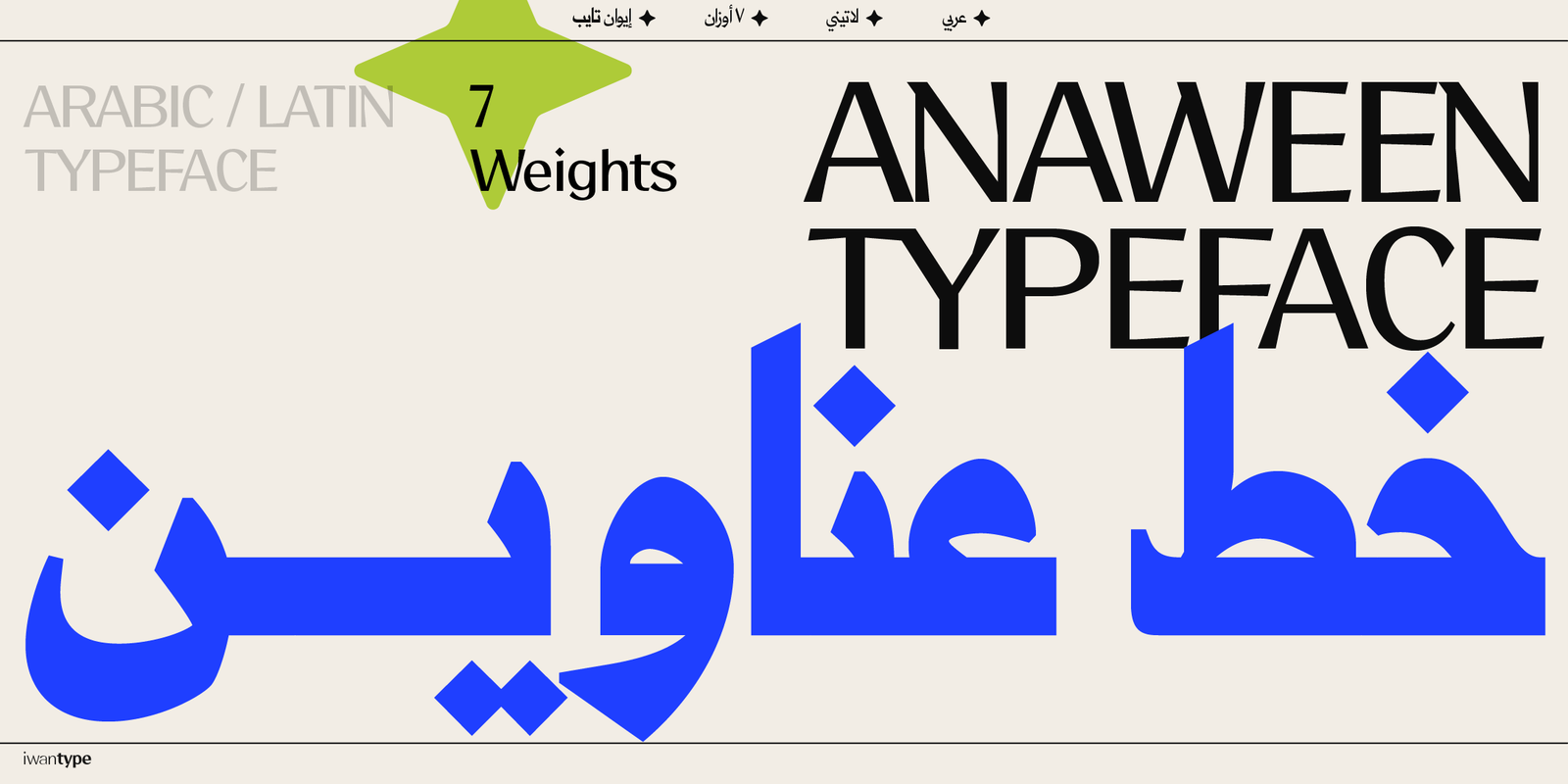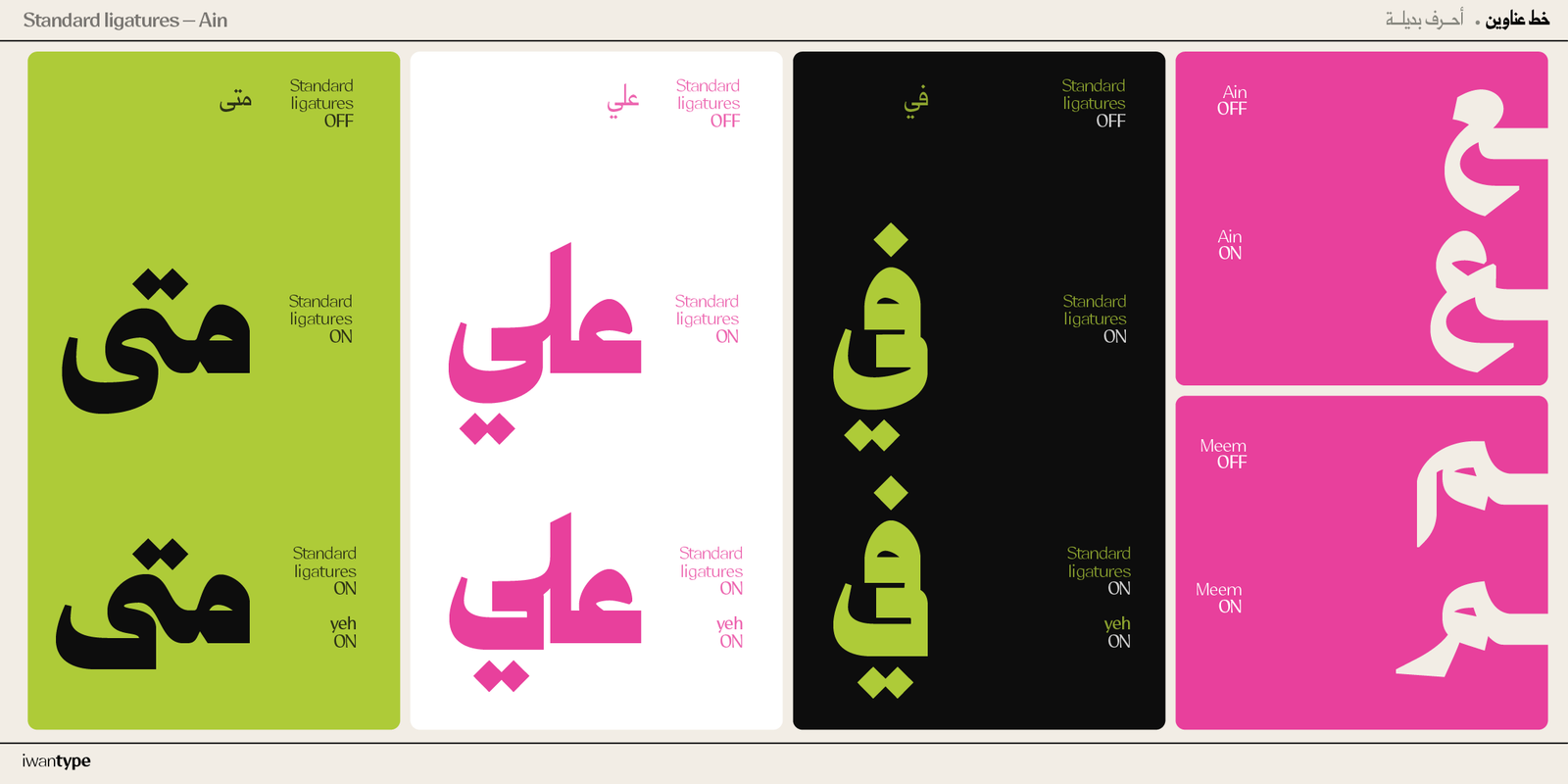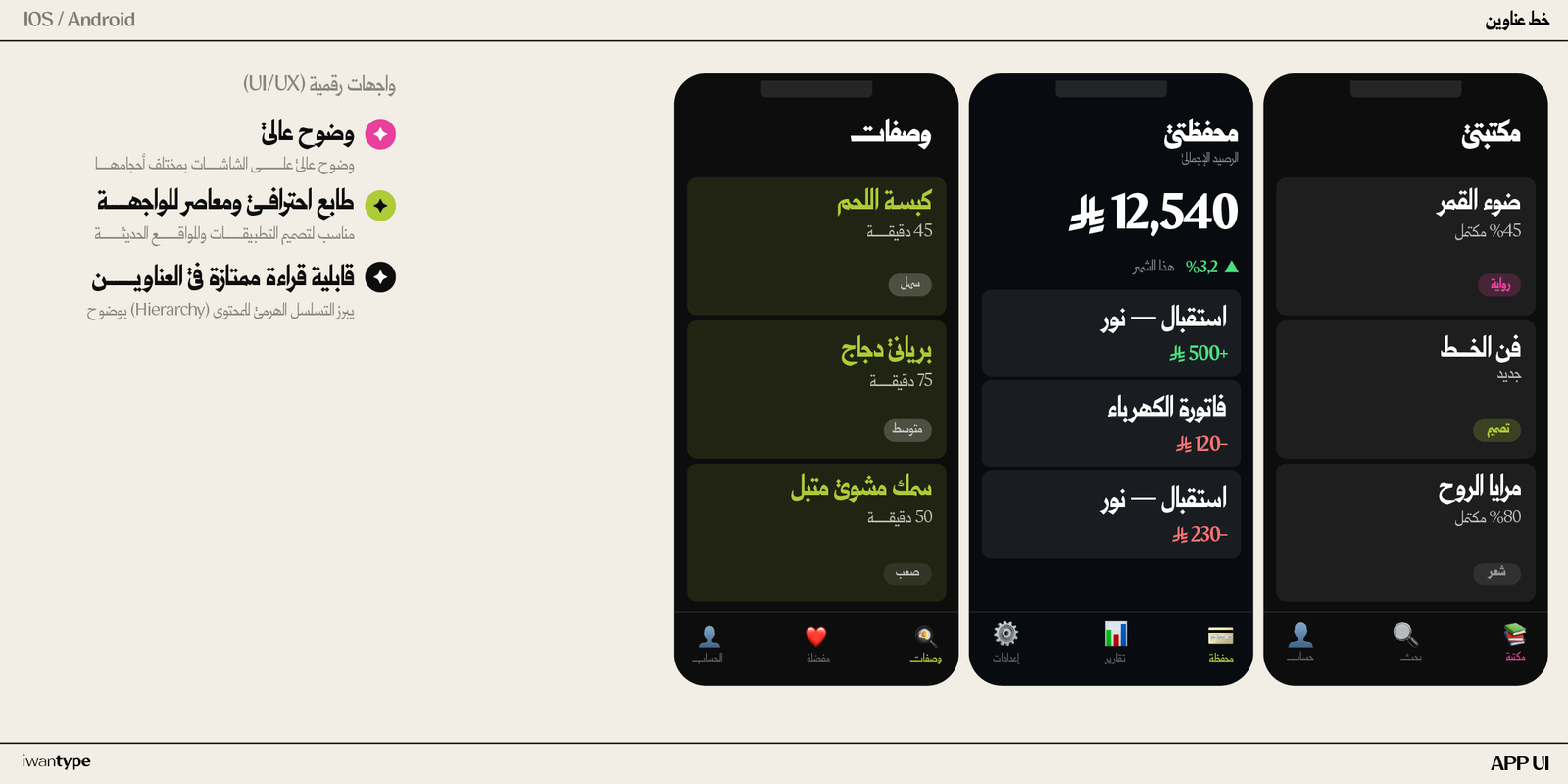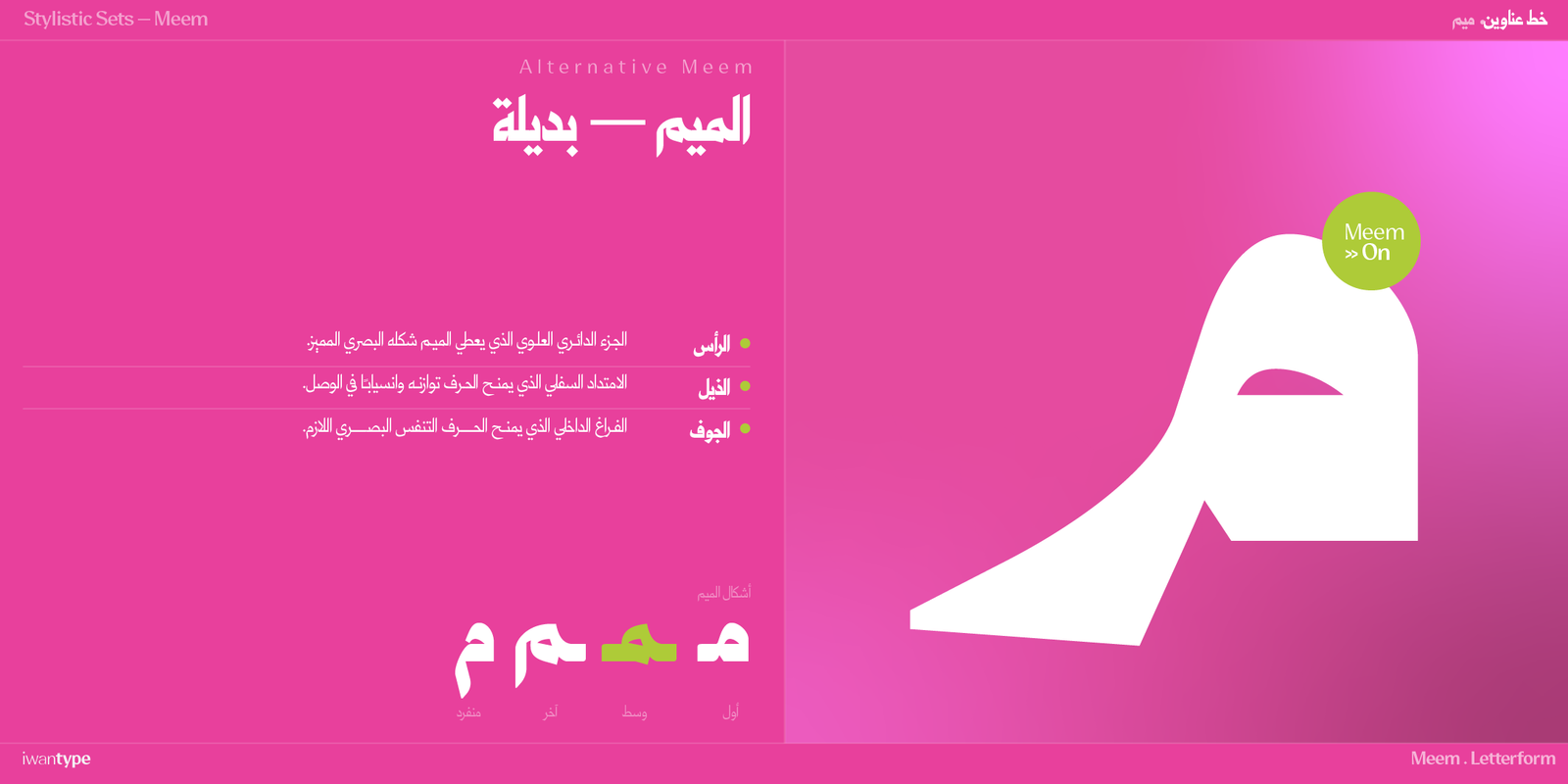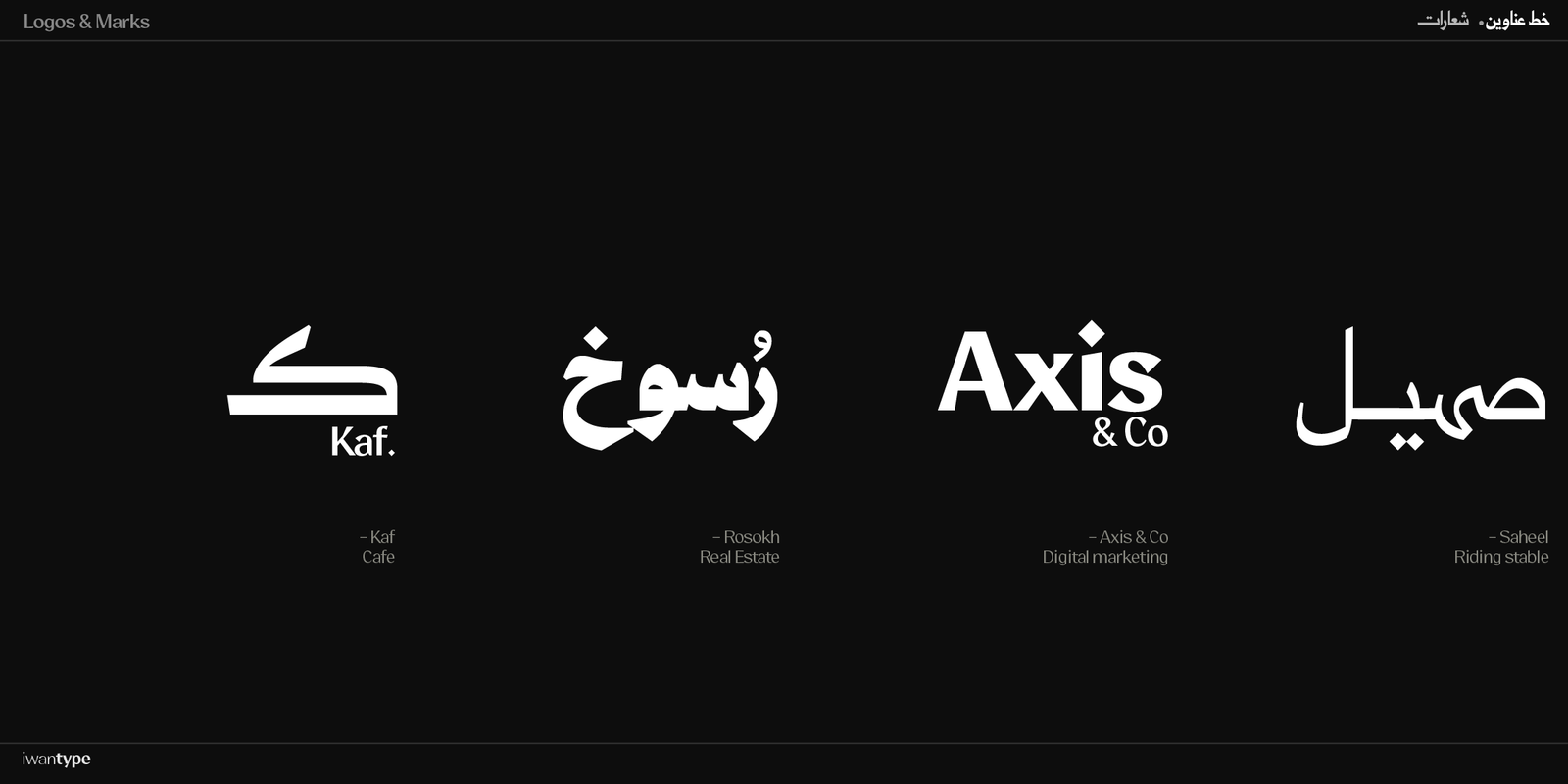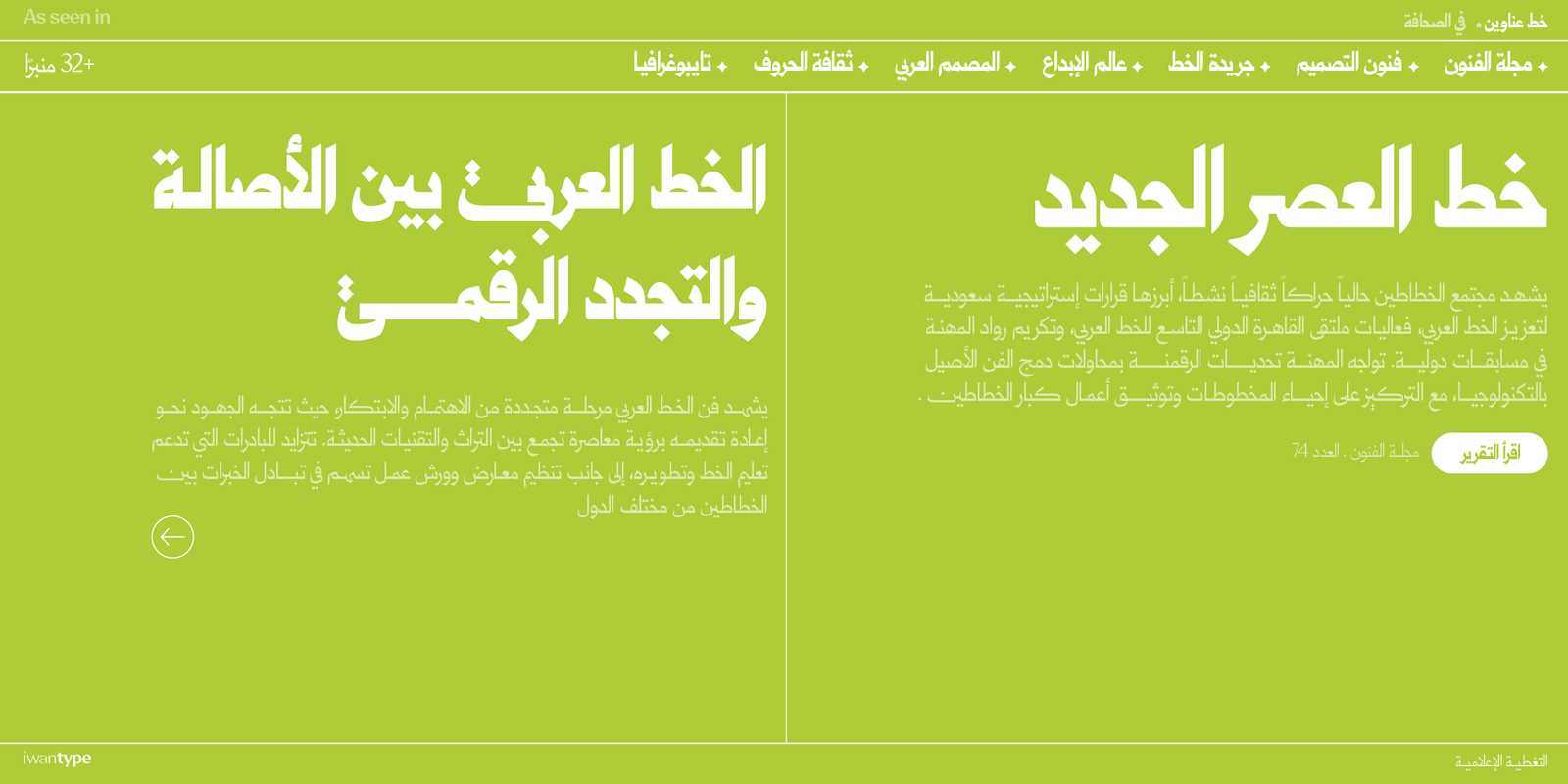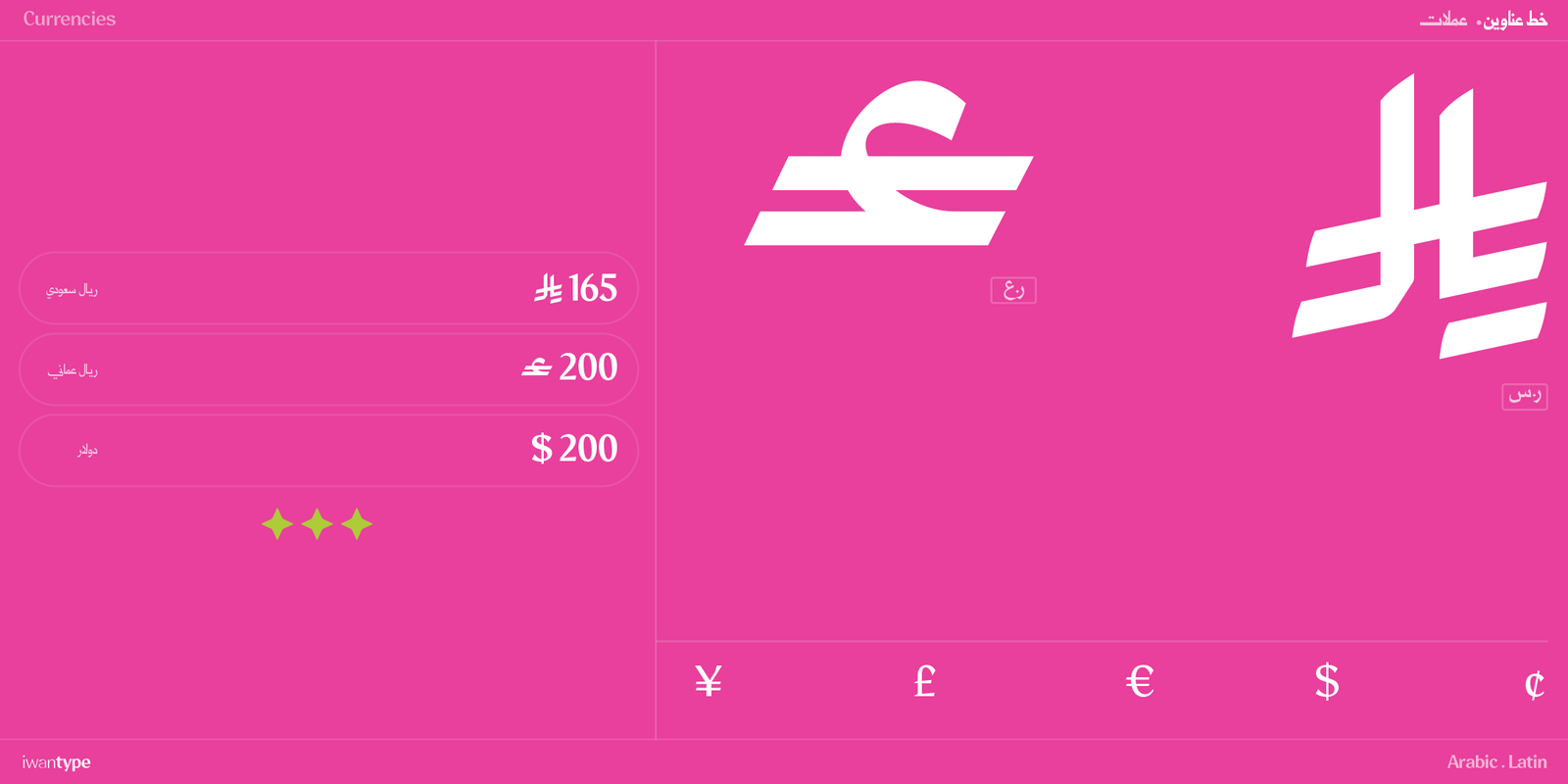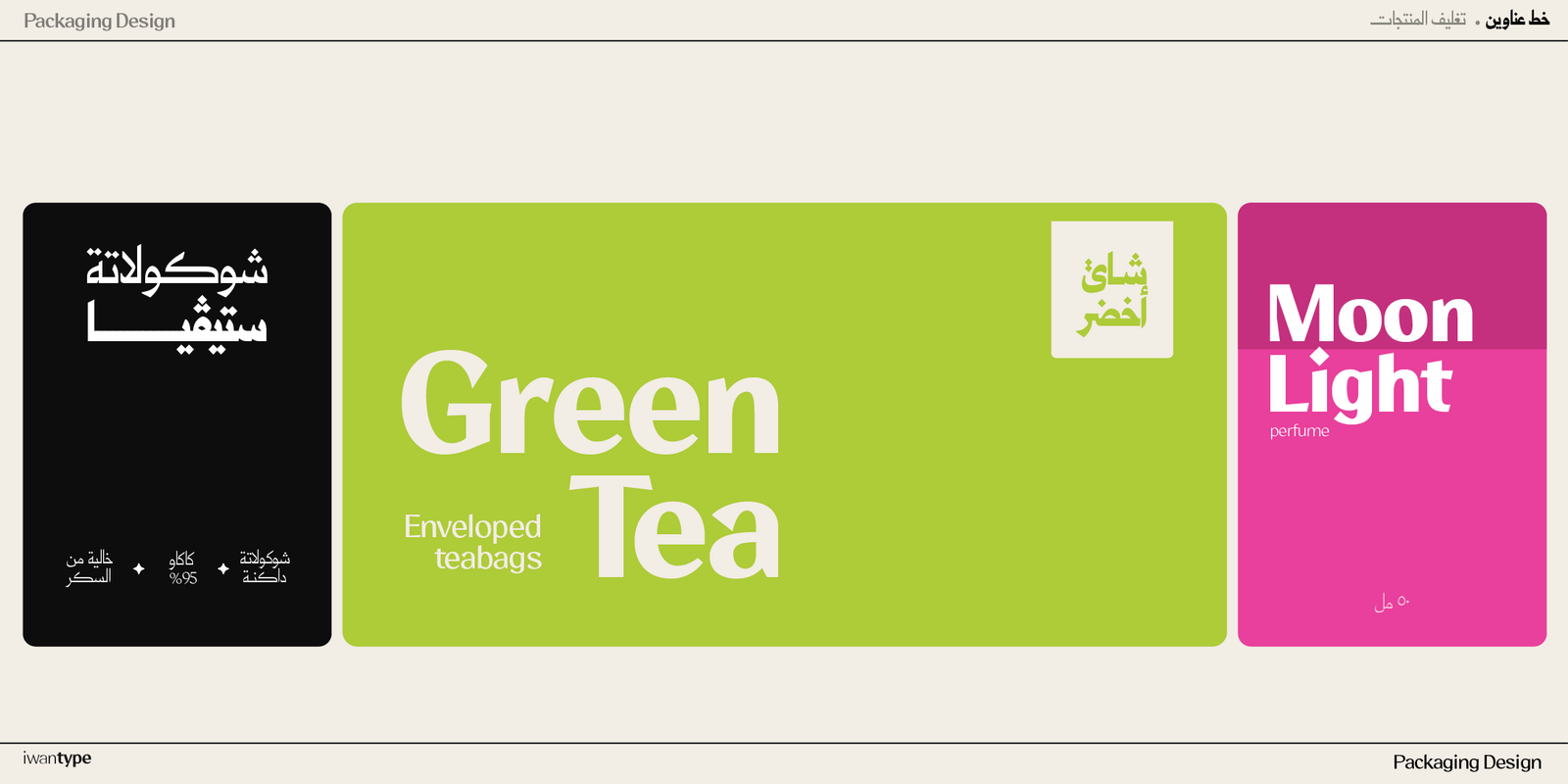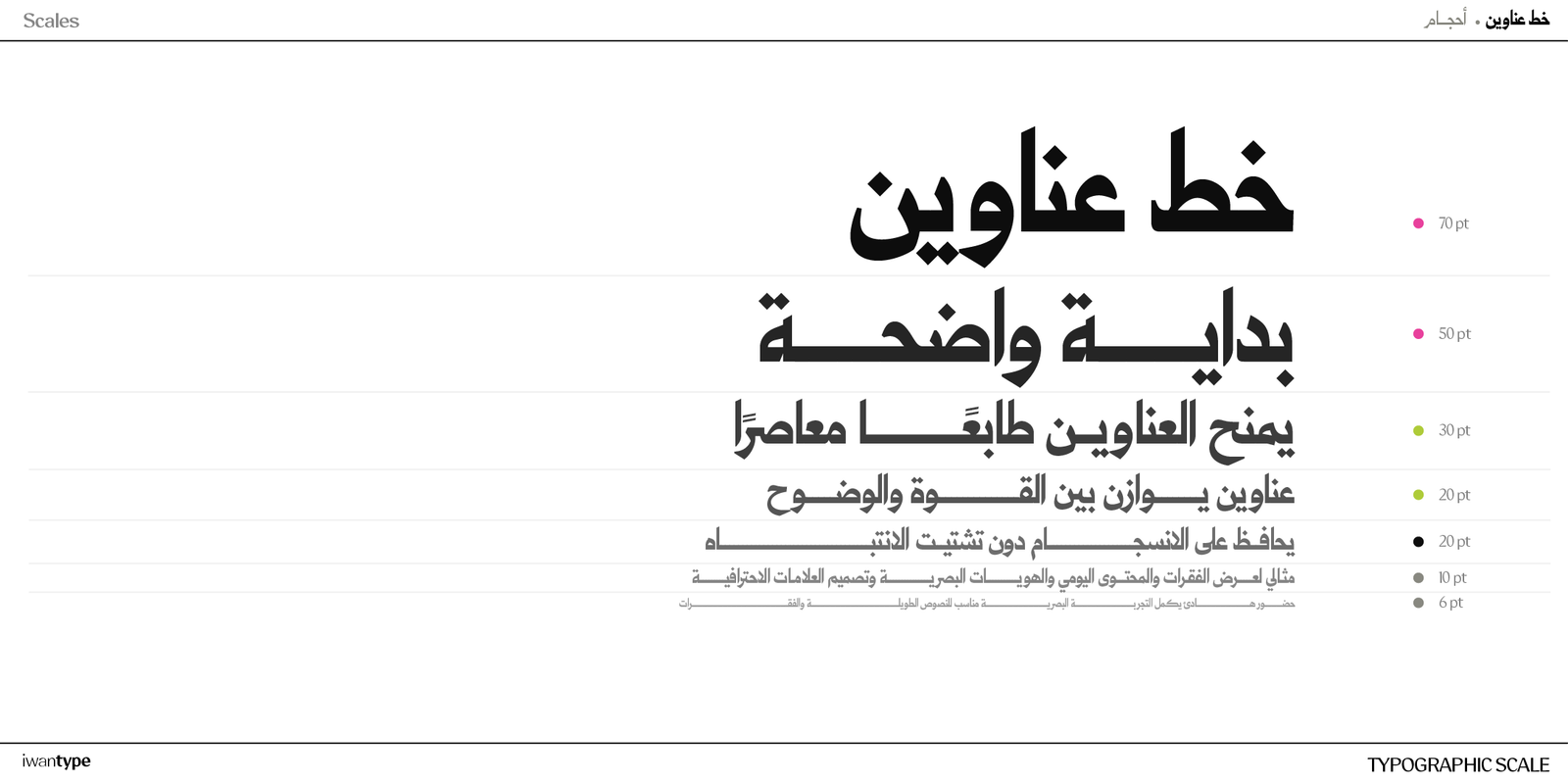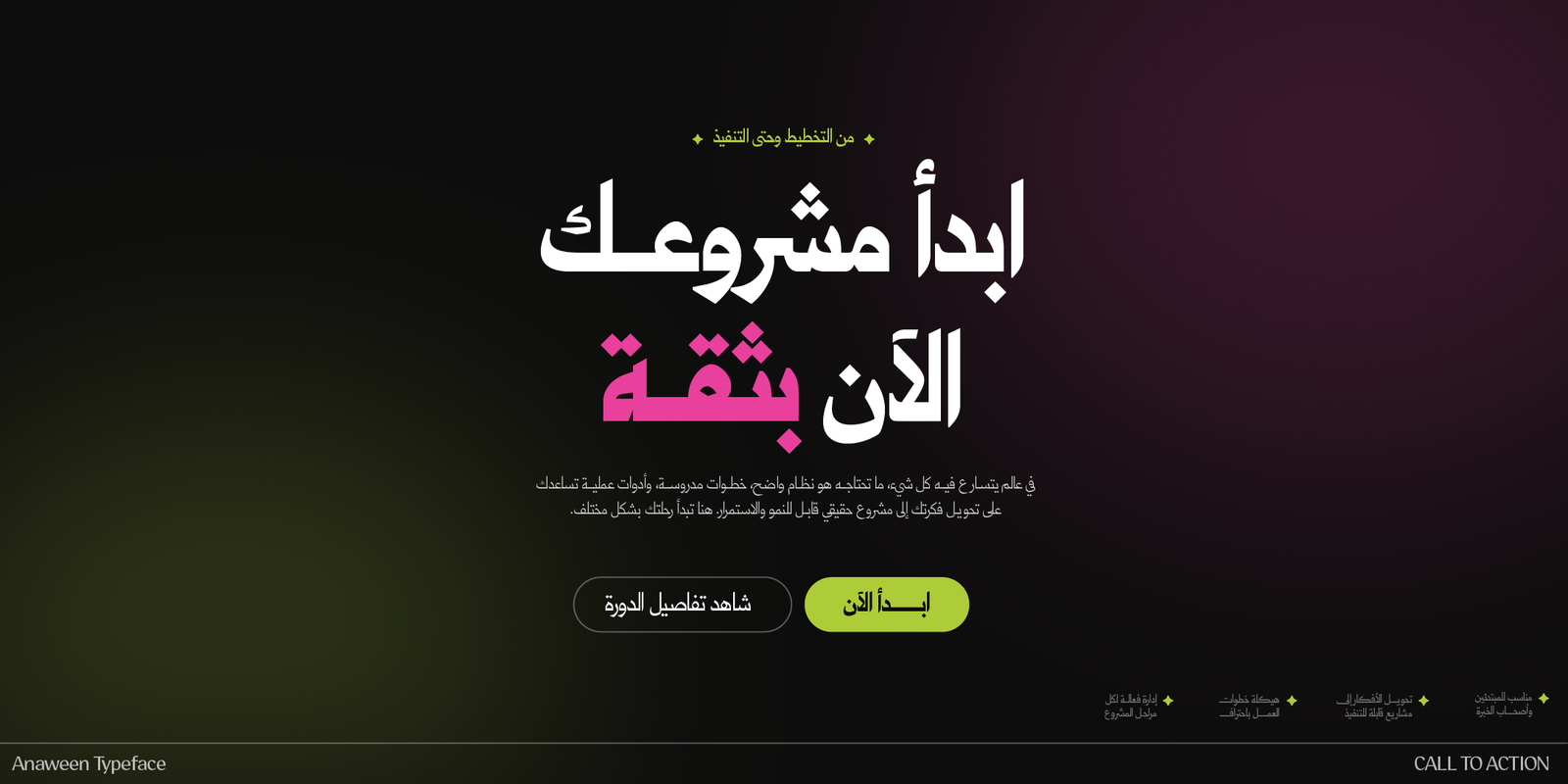
خط عناوين – Anaween Typeface – خط نسخ
خط نسخ طباعي بنسب رأسية ممتدة وتباعد بيني محكم، يستمد هويته من تقاليد خطوط الصحف والإعلانات.
يستند التصميم إلى منطق طباعي راسخ، اعتمد تاريخيًا على النسب الطويلة والتباعد الضيق لتحقيق أقصى كثافة بصرية داخل المساحة المتاحة. يُعيد الخط صياغة هذا المنطق في لغة معاصرة، تقوم على حروف ممتدة رأسيًا، وتباعد بيني مدروس، وهيكل مجرد من الزخرفة.
مميزات خط عناوين:
يتضمن الخط العديد من مزايا OpenType التي تضفي عليه مرونة وتنوعًا في الاستخدام، مثل:
- أحرف مرسلة (تُفعَّل بإضافة “ءء” بعد الحرف) لضمان عملها على Canva، والأجهزة المحمولة، والتطبيقات التي لا تدعم ميزات OpenType.
- حرف ياء بنزول أقل: يقلل من نزول السطر ويعزّز انتظام النصوص.
- أحرف مركّبة تُحسّن سلاسة التراكيب وتناسق النص.
- سبعة أوزان كاملة تمنح مرونة واسعة في الاستخدام الطباعي.
- يدعم رمز الريال السعودي والريال العُماني ،ويتم تفعيلهما تلقائيًا عند كتابة الاختصارات: ر.س للريال السعودي ر.ع للريال العُماني
اللغات: العربية والإنجليزية
الأوزان: ٧ أوزان